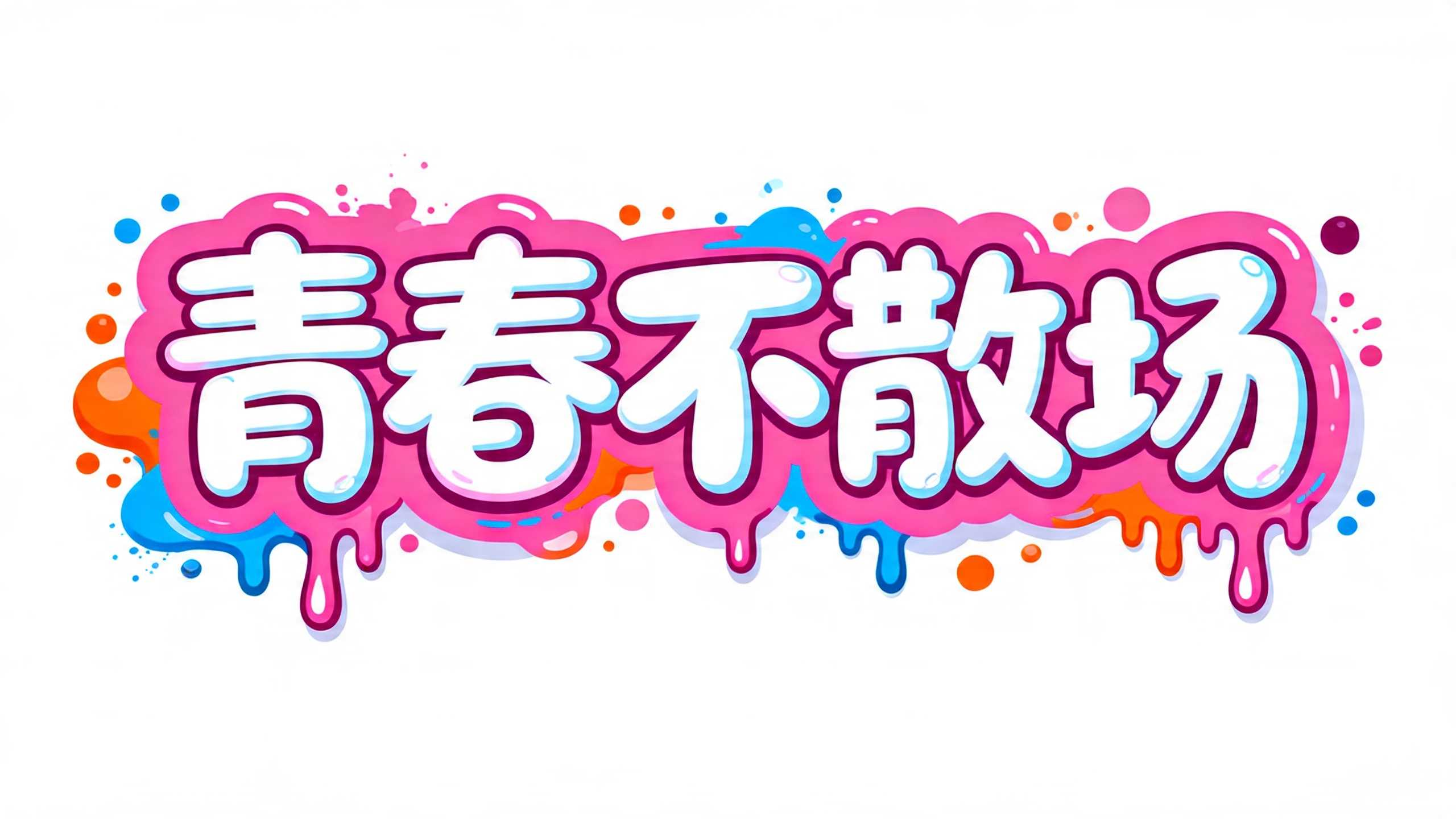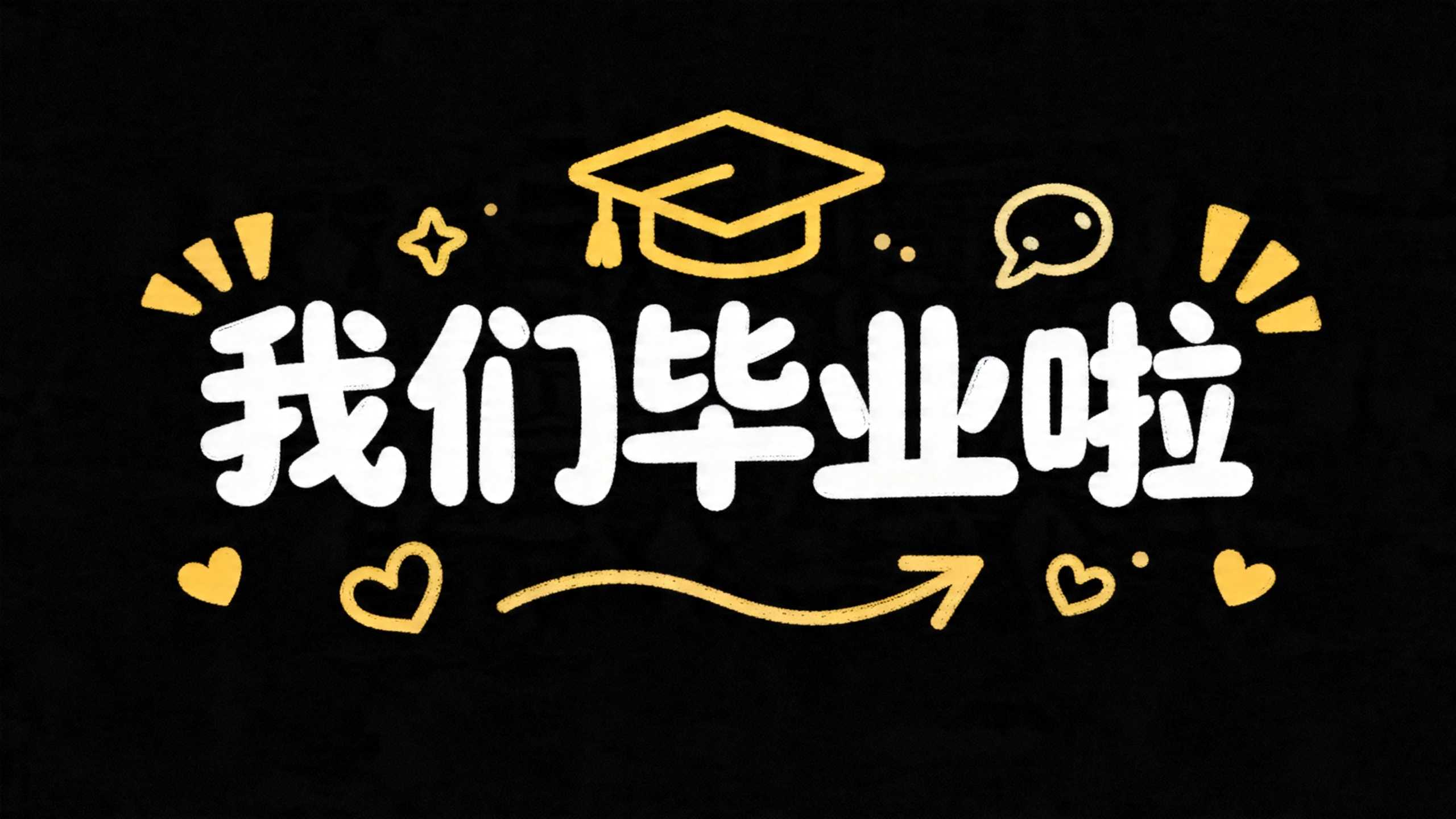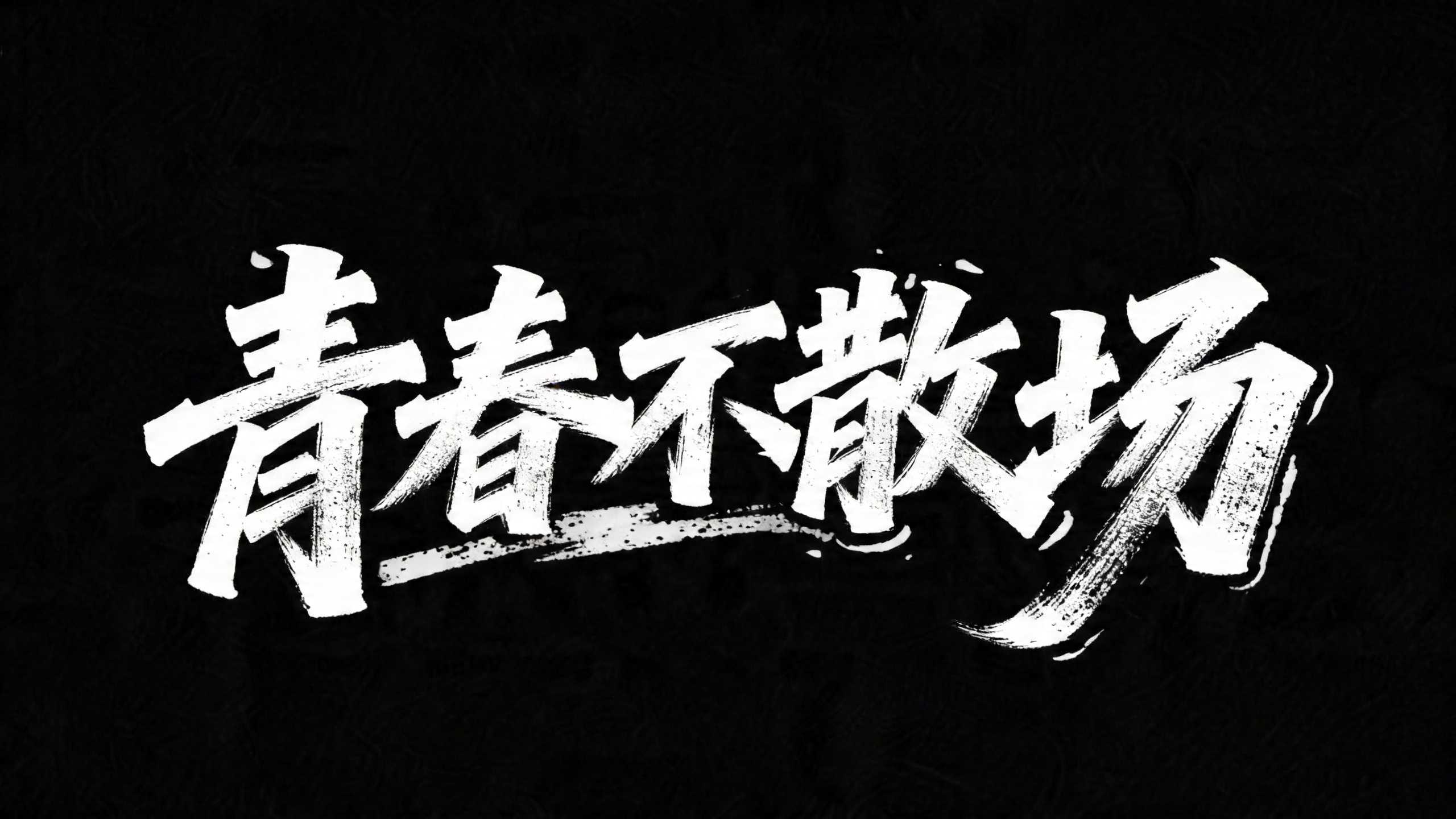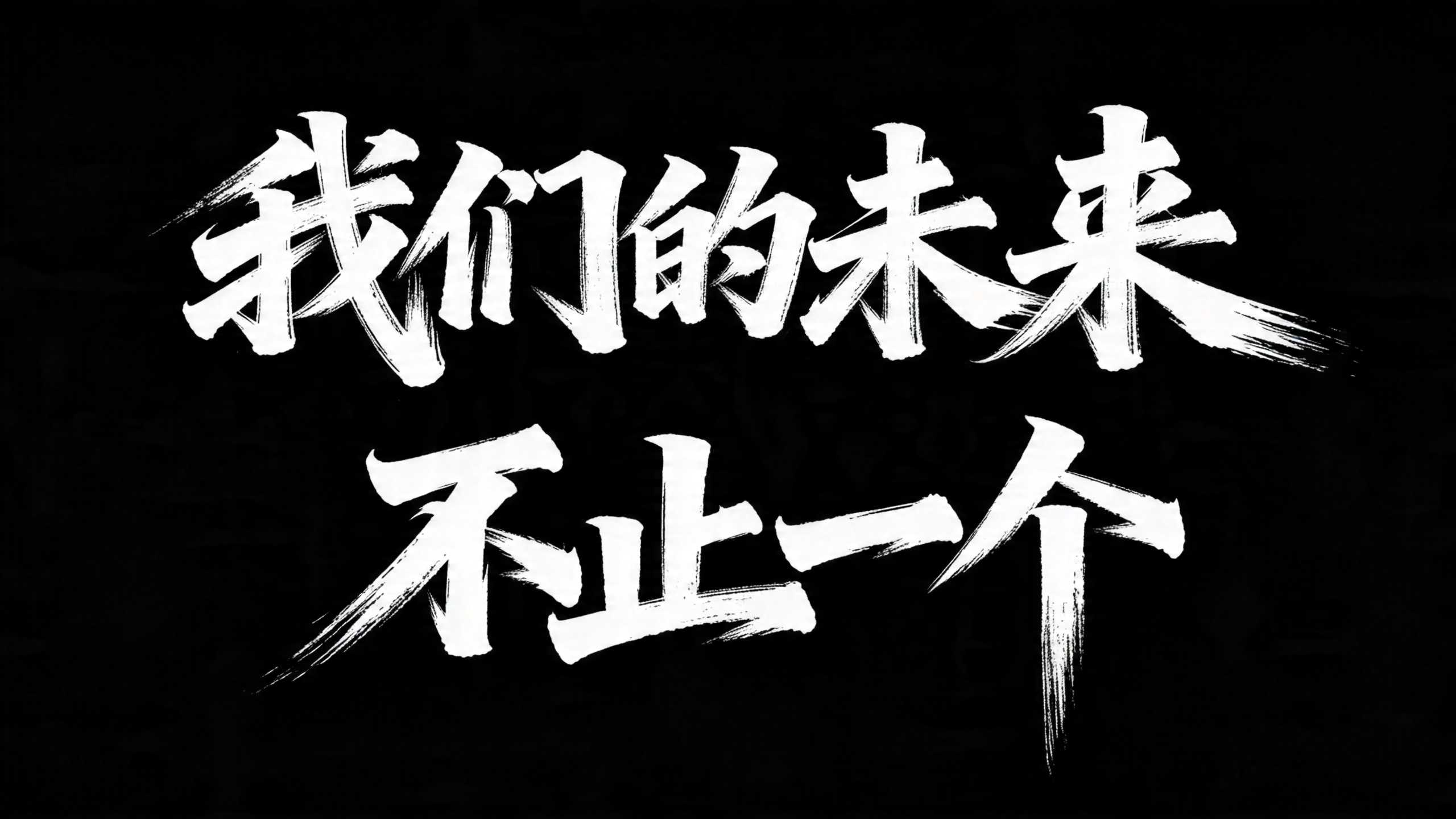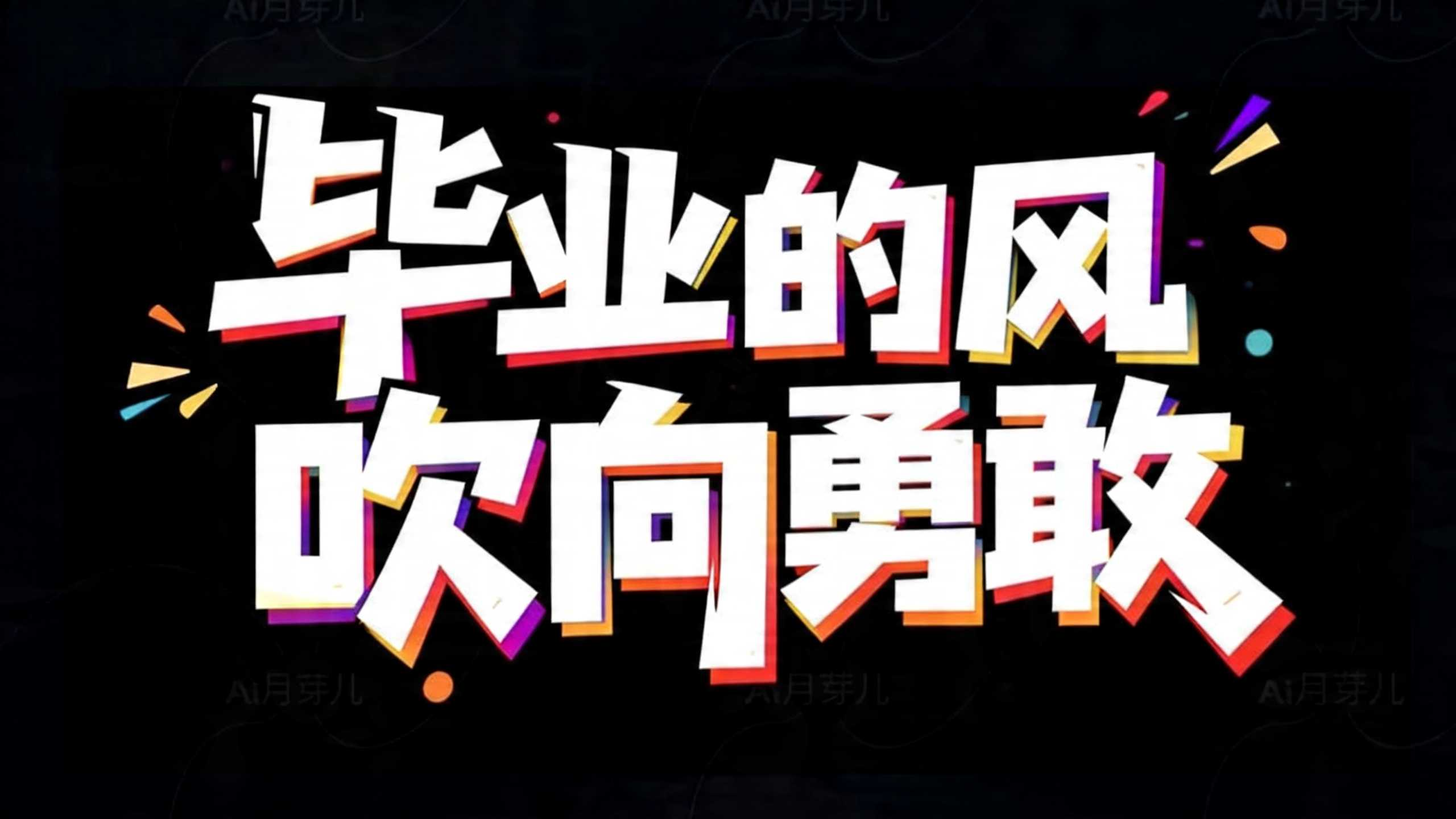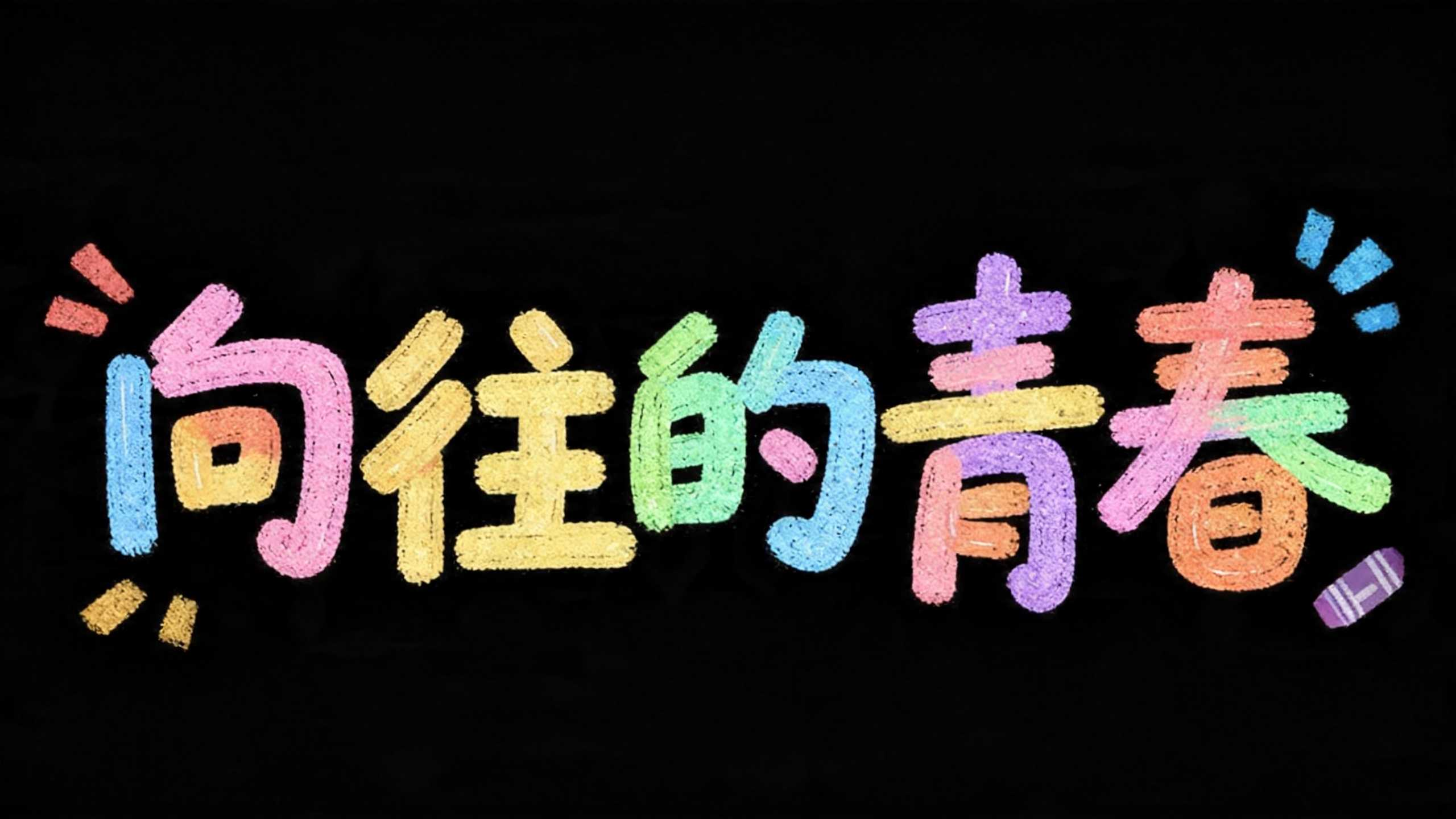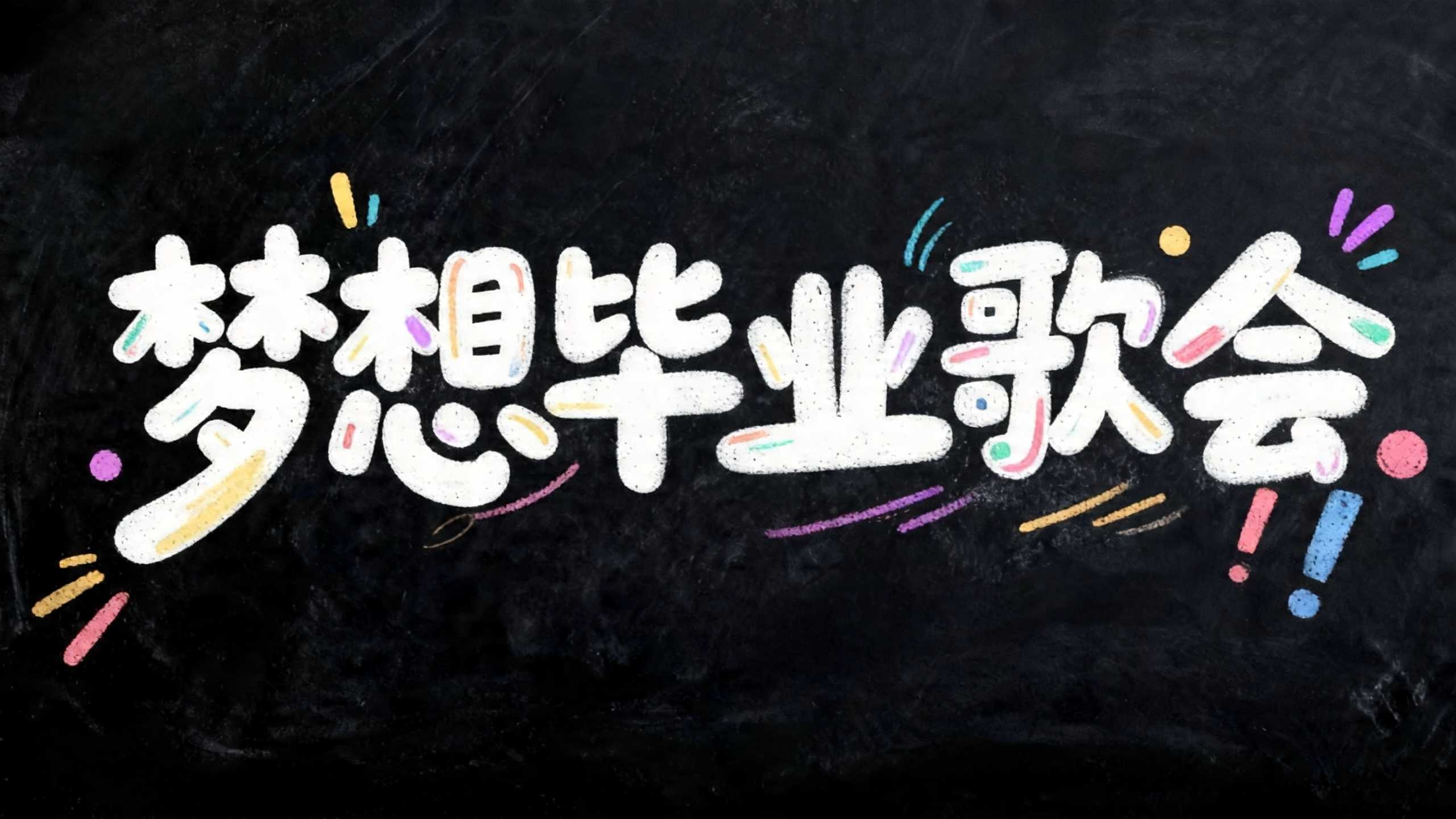
在这个属于离别与出发的毕业季,为大家分享七款超治愈的毕业季多彩校园风标题字体设计,一笔一画都写满了独属于少年的纯真与松弛。
一、彩虹糖果色粉笔涂鸦字体
设计特点:
采用高饱和度的彩虹糖果色渐变,色彩显得极其雀跃、活泼,带有强烈的视觉跳跃感。基于手写幼圆体的数字化变形,笔画圆润饱满,故意隐去了传统书法的锋利折角,线条粗厚且带有些许笨拙感。最核心的视觉在于粉笔颗粒肌理,笔画边缘和内部呈现出自然的磨损、飞白与擦染效果。文字左右两侧点缀了粉色与蓝色的放射状小短线,右下角还有一个紫色小蜡笔,增加了手作的趣味。
应用场景:
可以用于教师节、六一儿童节、母亲节、父亲节、感恩节等温馨节日主题,或用于校园主题快闪店主视觉、怀旧国货零食包装、文具品牌包装、K12教育培训海报等。
二、黑板报粉笔手绘字体
设计特点:
以大面积的粉笔白为主体色,保证了主标题在黑板背景下的绝对清晰度。但在字体的笔画内部、边缘以及四周的点缀元素上,局部融入了粉、黄、绿、蓝等彩色擦染。这种“主白辅彩”的配色既有视觉重心,又打破了纯白的单调。圆润的手绘感字体字形结构错落,大小不一,撇捺结构舒展。
应用场景:
适合用于音乐节、夏日露营节、文艺汇演、游园会等宣传海报,也可以用于Livehouse演出海报、独立音乐人专辑封面、文青风咖啡馆社群活动Banner、旅行Vlog片头花字等。
三、潮流感波普几何字体
设计特点:
对黑体进行了前卫的几何化重构。笔画末端多采用45度硬朗斜切,去除了所有柔和的圆角。字体带有微微的仰视透视感,并通过双层重叠拉出了超厚的立体挤压阴影。排版上采用紧凑的堆叠式组合,文字周围伴随有放射状的三角形和矩形破裂碎屑,气势张扬,动态感十足。
应用场景:
可以用于618或双11电商大促主标题、跨年盛典、周年庆、青年节等节日营销,也可用于创新论坛主视觉、电商首页焦点图 Banner 标题、说唱类综艺节目封面、数码新品发布会海报。
四、国风大气毛笔书法字体
设计特点:
行草书法的现代数字化演绎。字形整体向右上倾斜,带有强烈的动向与速度感。笔画粗细对比极为夸张,最醒目的是其枯笔与飞白特效。每一笔的收尾、折角以及长笔划都有大量的墨汁飞溅、拉丝和干枯的纤维感,充满运笔时的爆发力。
应用场景:适合用于高考誓师大会冲刺海报、国庆节主视觉、元旦跨年新媒体配图,也可以用于武侠手游主视觉标题、国潮服饰印花设计、热血动漫主视觉、运动品牌燃系广告KV。
五、可爱手帐简笔画插画字体
设计特点:
纯白色的文字主体,搭配暖黄色涂鸦装饰,温暖、干净、不聒噪,具有很强的呼吸感。风格偏向日系便签手写体。字形偏扁、重心偏低,横竖笔画粗细几乎一致,有种用粗马克笔在纸上随性写字的松弛与可爱感。文字上方巧妙融合了相同线宽的学士帽简笔画,四周环绕着心型、星光、聊天气泡和波浪箭头。
应用场景:
适合用于母亲节暖心感恩文案、治愈系视觉、感恩节营销,也可用于生活方式品牌小红书封面图、独立咖啡馆烘焙店海报、个人Vlog日常手帐素材、情感类播客封面设计。
六、国潮霸气手写毛笔字体
设计特点:
狂草与现代字形设计的结合。字形极其扁宽,视觉重心压低,字与字之间通过强烈的笔画交叉和重叠连成一个整体。最下方的横向拉丝枯笔形成了一条稳固的底座线,右侧“场”字的最后一撇化为巨大的飞白扫刷痕迹,打破了字体的方正边界。
应用场景:
适合用于建军节、五四青年节热血文宣,也可用于健身房海报主视觉、汽车商业广告片标题、国潮金属风配饰品牌VI、竞技类电子竞技赛事海报。
七、潮流街头涂鸦立体字体
设计特点:
使用极其大胆的多层色彩撞击,色彩之间不进行细腻过渡,而是呈现块状或喷溅状的重叠,极具波普艺术的冲突感。字体用胖胖的泡泡一般的字体变形,字体结构完全圆润化,笔画如充气般膨胀,带有明显的白色亮光与高光结构,营造出类似果冻的微3D视觉。字形外围做了双层粗描边,最底层融合了液体下滴与圆形颜料喷溅的特效,街头感拉满。
应用场景:适合节日活动、电商活动标题或是音乐节的视觉设计,也可以用于街舞说唱等潮流综艺的主视觉、潮流玩具包装、个性彩妆联名款包装等。